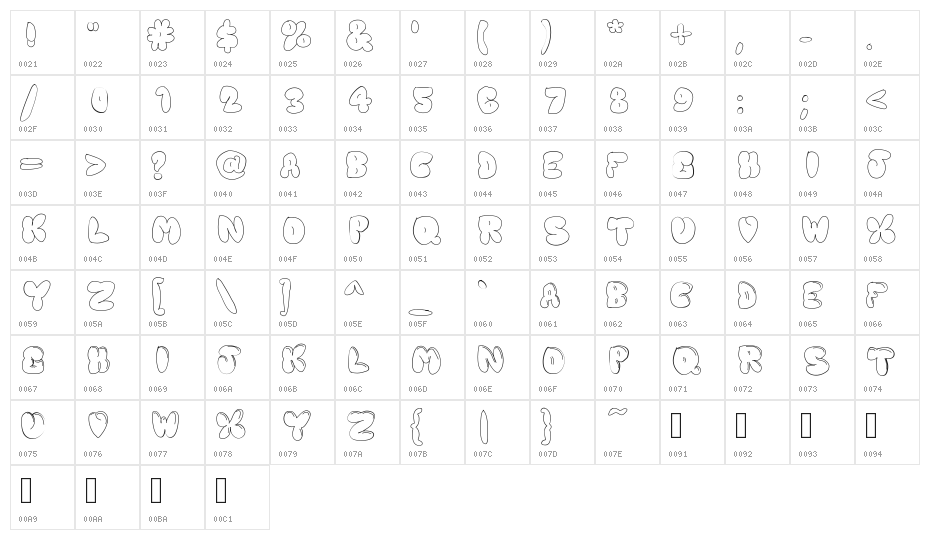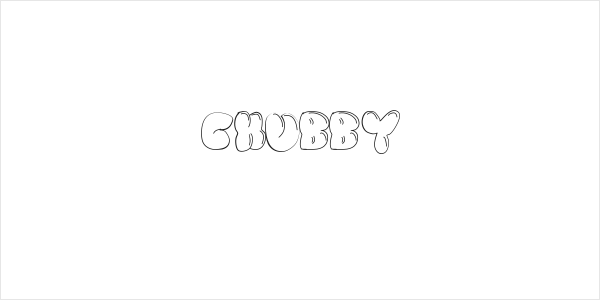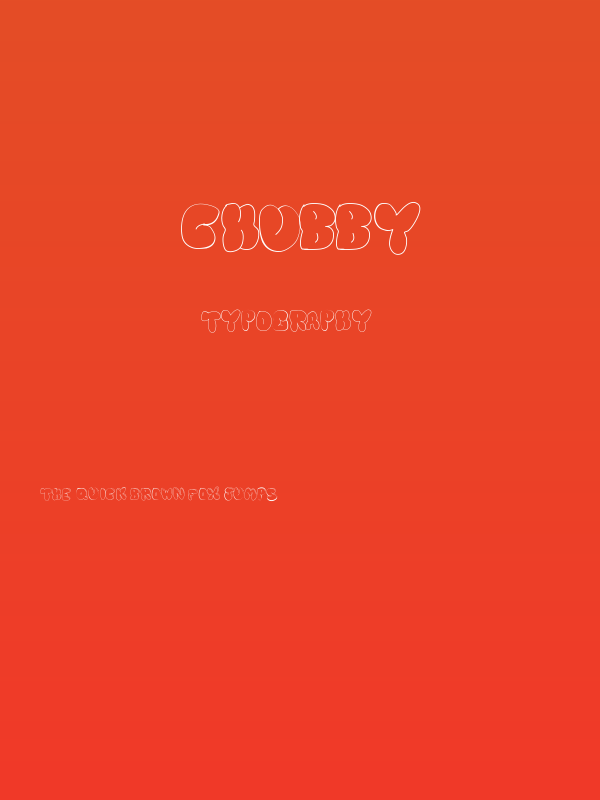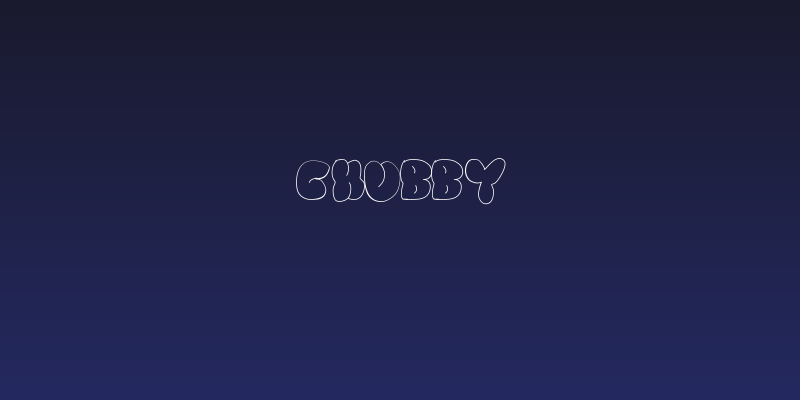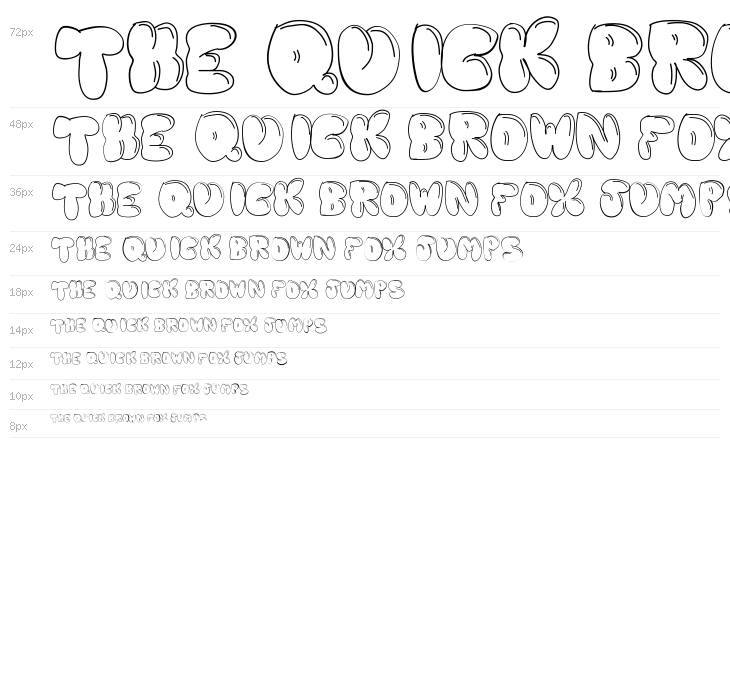
Chubby Font
| Gesamtstil | Playful, Fun |
| Vorgeschlagene Projekte | Ideal for children's books, playful branding, party invitations, and creative posters. |